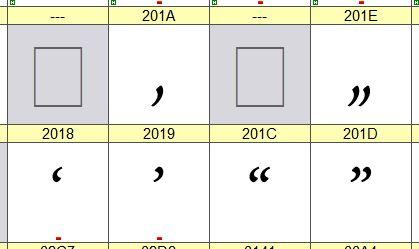
Falsches Anführungszeichen Arno Pro
ich habe zusammen mit der CS 3 ein Schriftenpaket mit u.a. der Arno Pro erworben. Leider sind bei der Regular und Semibold die falschen Anführungszeichen (entsprechen der Anführung in der Kursiv) enthalten. Das ist eindeutig ein Fehler von Adobe. Nur leider kann man die nicht mehr anfragen bzw. wird - sehr nervig - in einer Schleife "zurück auf Anfang" gesetzt. Nicht mal eine Postadresse gibt es noch bei denen.
Muß ich die Schriftschnitte neu kaufen (mit hoffentlich richtigen Anführungen) oder gibt es eine andere Lösung?
Von wann genau ist die Schrift datiert?
Ich hab mit die ArnoPro mal angesehen, da sind wirklich bei ALLEN aufrechten Schnitten die unteren Anführungszeichen unterschiedlich in der Form zu den oberen also auch in Bold in allen Entwurfsgrößen, also Text, SmText, Subhead, Caption, Display.
Font-Erstellungsdatum steht in diesen 2007
Ich habe mit der Arno noch nichts gemacht, aber wenn ich bei mir nachschaue, dann scheint das hier auch so zu sein. Wenn das so ist, dann kann ich mit der Arno wohl auch in Zukunft nichts machen.
Das Problem besteht in den aktuellen Versionen nicht mehr. Die Frage ist also nur, wie man an ein Update kommt, wenn man keinen Direktzugriff auf aktuelle Versionen wie durch Typekit hat.
Stimmt, ich habe es gerade ausprobiert. Da komme ich jetzt aber nur an die vier Schnitte der Arno Pro. Meine anderen 28 Schnitte (Caption, Display, Small Text und Subhead) werden aber nicht zur Synchronisation angeboten.
Was heißt das jetzt?
Ich hatte die Arno mit der CS3 bekommen als incentive, wenn ich mich recht entsinne. Mir wurde damals ein Update der ganzen Suite angeraten. Einzelne Fonts würde Adobe nicht updaten, sofern sie mit der CS mitkommen. Vielleicht sieht es anders aus, wenn man sie einzeln gekauft hat?
Wir haben hier jetzt auch nur noch CC, weiß jemand, ab welcher CS-Version die Anführungszeichen richtig sind?